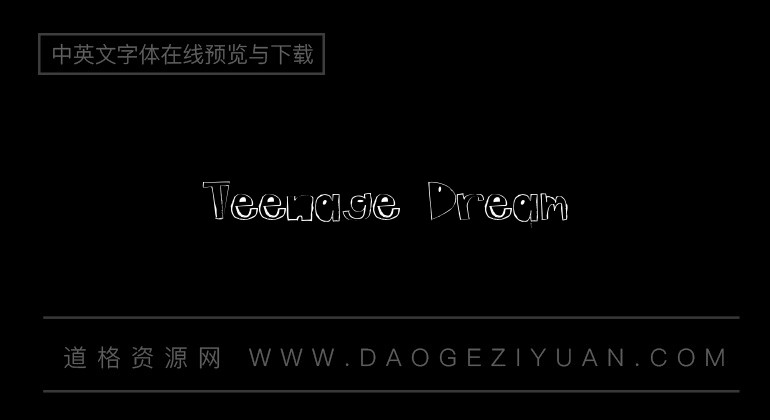
Teenage Dream 是一种英文字体,它的设计灵感来自于流行音乐、流行文化以及青春时代的回忆。这种字体的特点是有点圆润、柔和,同时又不失清晰、鲜明。它的字母间距和行距比较紧凑,让文字看起来更加紧凑、流畅。此外,Teenage Dream 字体还带有一些手写体的特点,比如一些字母的笔画有点弯曲,让整个字体看起来更加活泼,富有青春气息。 这种字体常常被用来设计广告、海报、音乐封面、卡片等等,尤其是那些与青春、活力、梦想等主题相关的设计。它的使用可以营造出轻松、愉快、充满活力和激情的感觉,非常适合表达年轻人的精神和态度。内容介绍
Teenage Dream是一款非常不错的手写艺术字体,具有很好的视觉感,适合于文化类的宣传设计、商业类品牌的广告和产品包装设计以及个性化文字排版等较多场景。